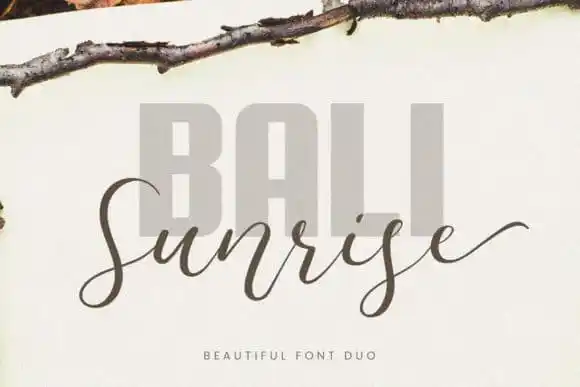
Bali Sunrise Calligraphy Font – Download Grátis
A Bali Sunrise Calligraphy Font é uma beleza de tipografia moderna, inspirada na elegância dos designers hoteleiros e resorts. Ela traz uma perfeição incrível nos caracteres, mantendo um encantador fluxo que promete deixar sua impressão digital do jeito que merece ser feita: sofisticada e única. Desenvolvida pela font designer Auratype, a Bali Sunrise possui acabamentos perfeitamente finos nas extremidades dos caracteres, criando um aspecto quase esculpido. Este é o tipo de fonte que vai tornar seu texto de design mais atraente e imponente, permitindo combinações perfeitas. Seja para gráficos digitais ou publicações impressas, ela traz uma atmosfera leve que certamente será encantadora para quem a usa. Através da Bali Sunrise Calligraphy Font, você encontrará um novo nível de sofisticação e originalidade em seus projetos.